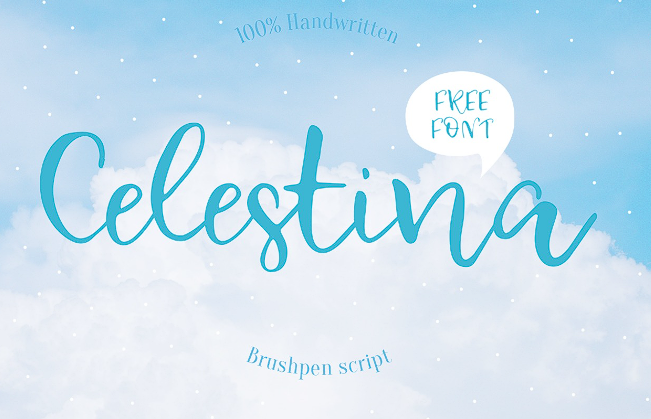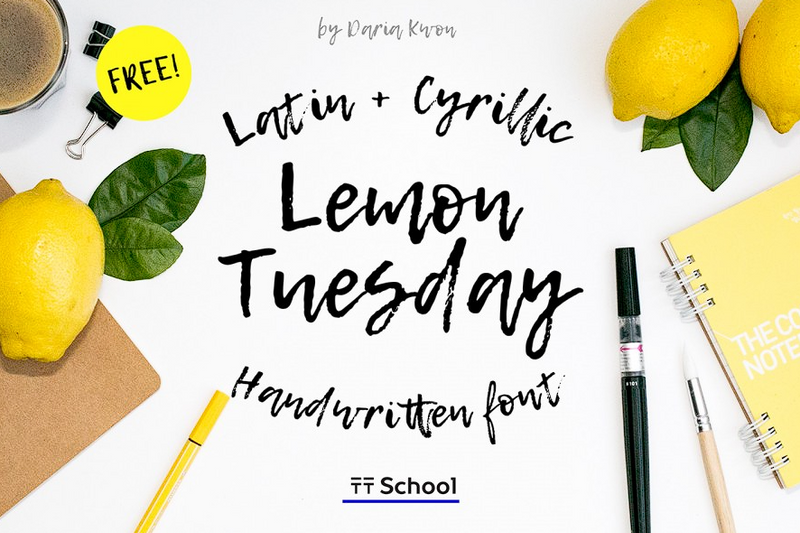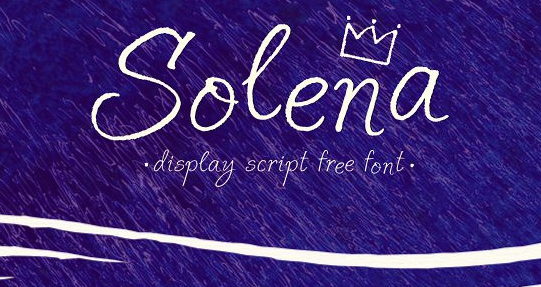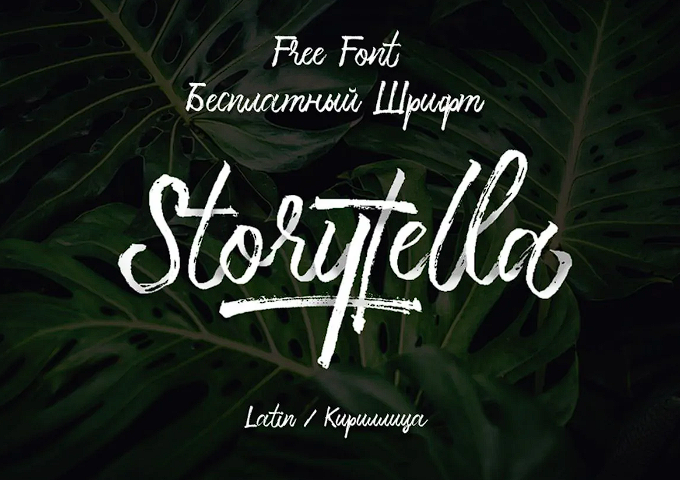
Безкоштовні рукописні шрифти з підтримкою української мови
Lemon Tuesday
Красивий рукописний шрифт, з безкоштовною ліцензією. Шрифт початково був орієнтований на короткі емоціональні надписи, але на мою думку, він ідеально підійде для заголовків, постерів, соціальних мереж, тощо.
Celestina
Повітряний та легкий шрифт. Підійте для листівок, заголовків. Я вважаю, що краща тематика для Celestina це весілля, або річниці.
Solena
Надзвичайний шрифт, який дуже нагадує море, сіль, подорожі та літо. Підійде як раз таки на тематику з перших асоціацій про Solena. Назва кричить сама за себе.
Storytella
Цей шрифт було намальовано пензликом. Має багато альтернатив у використанні. Підійде для постерів, картинок, заголовків. Тож хай ваша фантазія використовує його як тільки заманеться.
Sweet Mavka Script
Казковий шрифт, дуже містичний (по назві). Хочу зазначити, що цей шрифт можна використовувати у великих розмірах. Підійде для оформлення різної айдентики, накладення на фото, заголовків, оформлення, тощо.